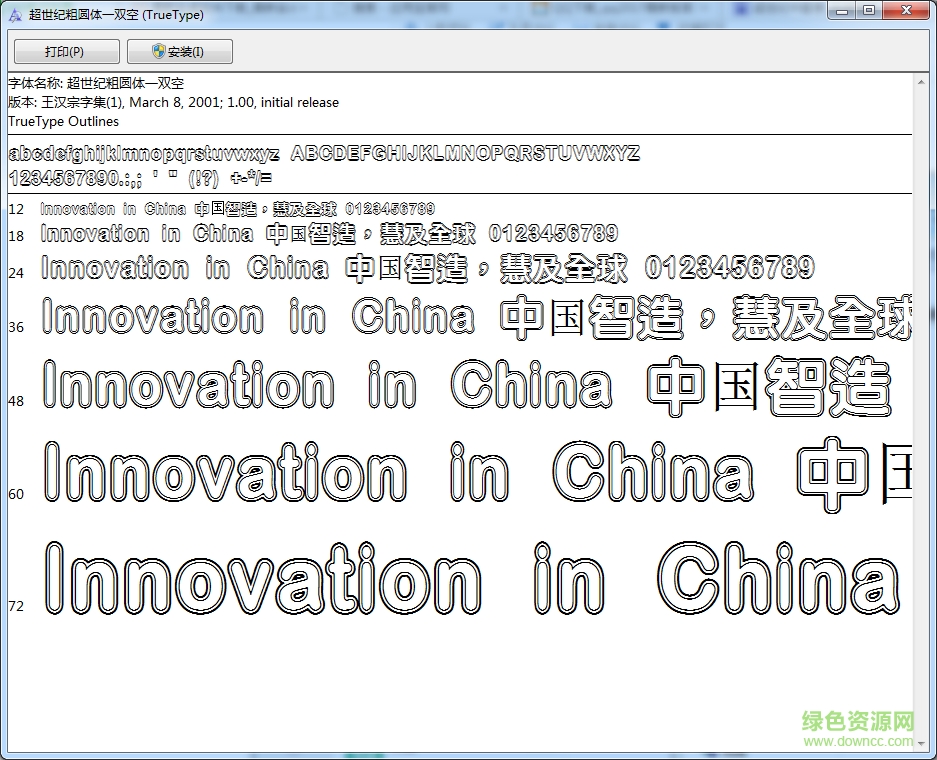
超世紀(jì)粗圓體雙空字體是一款非常別致的空心字體,空心字體看起來(lái)十分的俏皮活潑,很適合放在自己作品里面增加點(diǎn)氣氛,以空心為主要風(fēng)格非常適合于電腦字體設(shè)計(jì)中使用??靵?lái)綠色資源網(wǎng)下載體驗(yàn)吧!
超世紀(jì)粗圓體雙空字體是超世紀(jì)字體庫(kù)中一種字體,常用于美工設(shè)計(jì)方面,喜歡的朋友不要錯(cuò)過(guò)。